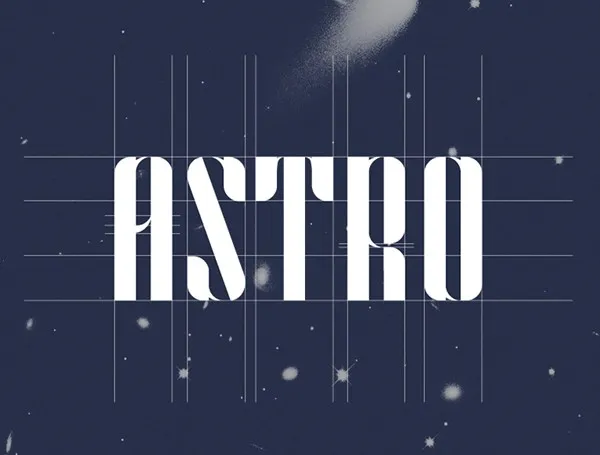
Astro é uma fonte modular criada pelo designer Hamilton que nos traz inspiração do universo celeste. As formas iniciais foram inspiradas por elementos astronômicos, fazendo com que toda a experiência criativa seja influenciada por este campo de fascínio. Este primeiro lançamento de Hamilton explora as linhas e os detalhes que emergem da astronomia, resultando em uma fonte única que se destaca tanto quanto o universo no qual ela é inspirada. Seja em um texto formal ou informal, Astro oferece uma sensação visual que flui naturalmente à medida que você desliza seu olhar pela página, criando uma experiência de leitura cativante e fluida. Visite nossos canais para explorar ainda mais a estética e o universo da FlowArt: http://www.behance.net/flownart, http://www.flownart.tumblr.com e http://www.instagram.com/flownart. Descubra e se inspire com Astro Font, uma fonte que faz as coisas um pouco diferentes em cada página de texto.